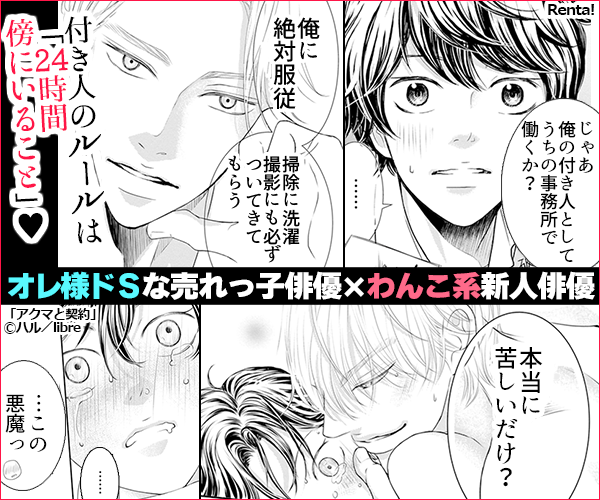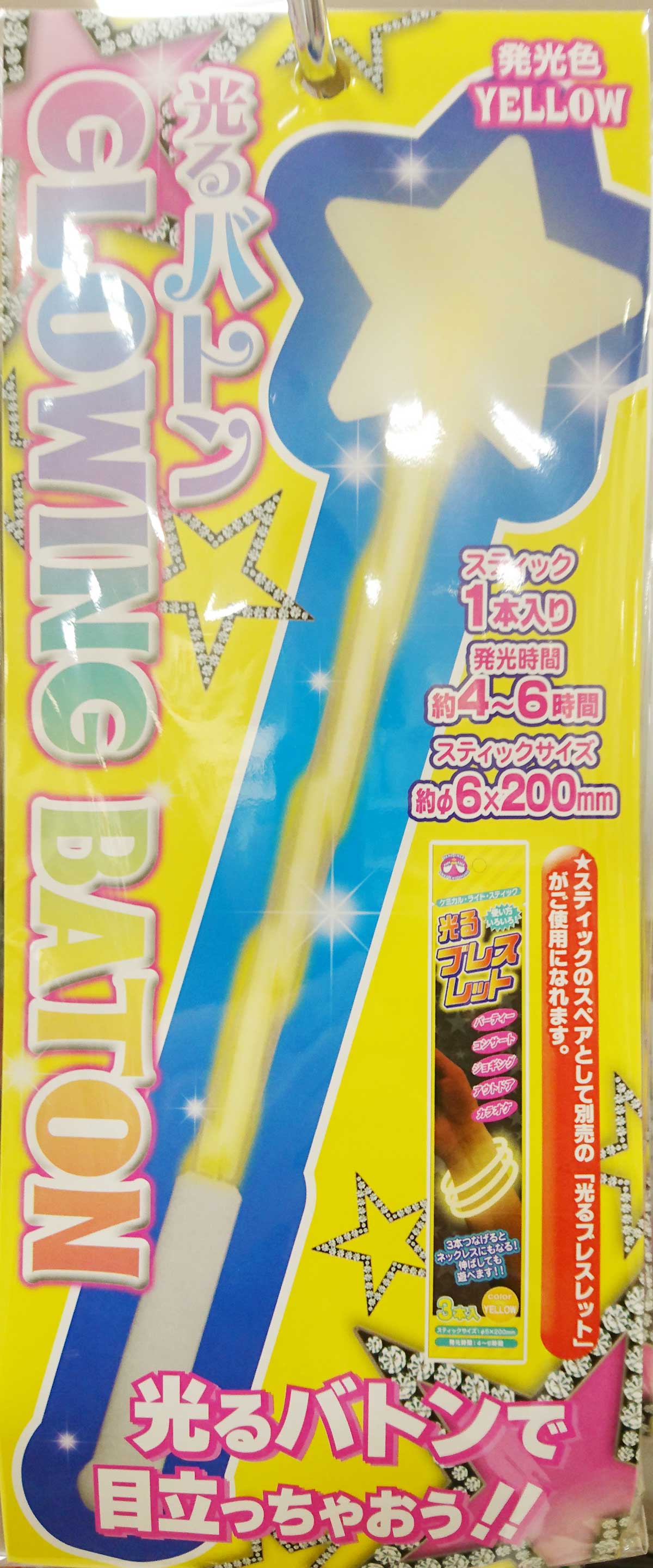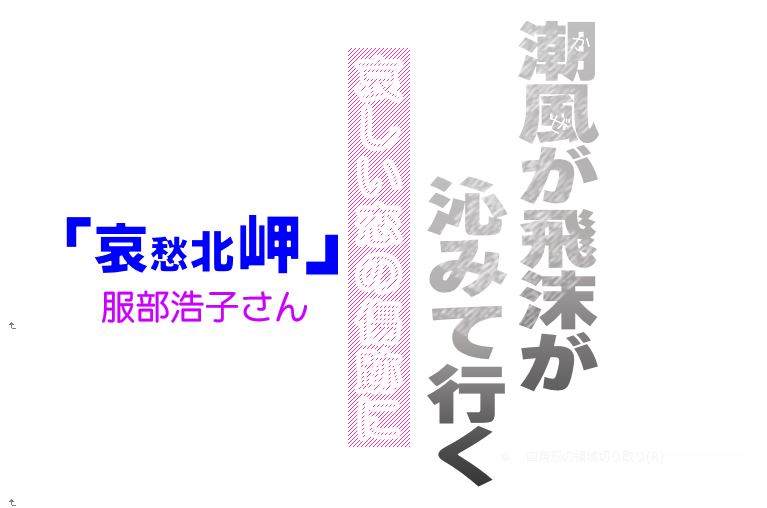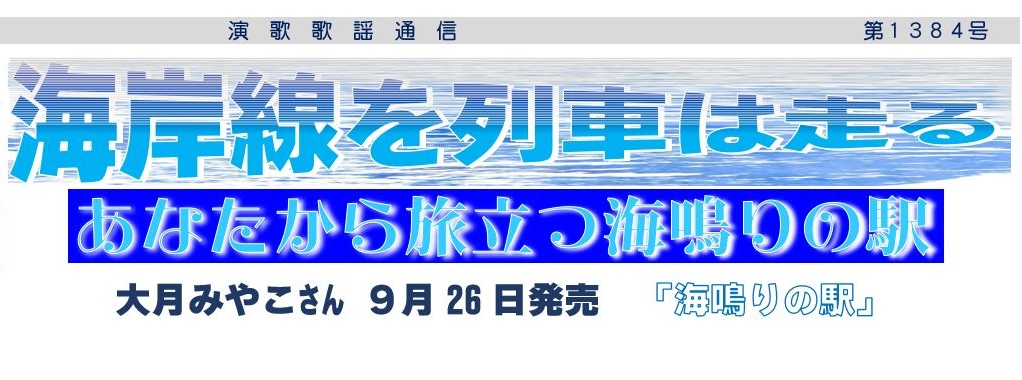
上下の太い文字部分。
「東リベ」27巻発売記念“実現して欲しいグッズ”投票。
地元のショッピングセンターで見かけたカプセルトイのPOPで「ルイカ-09」が使われていました。
「プラモデル塗装には〜ミニチュアキーチェーンに!」の文字ですね。
その下の色の名前も、おそらくルイカですね。
Adobe Fonts経由かもしれませんが、こうして使用例が増えていくのはウレシイ限りです。
「ここなの研究所」という、「鬼滅の刃」に関して考察しているYouTubeチャンネルです。
動画内やサムネイルなどで「ルイカ-09」がたくさん使われています。
Adobe Fontsの仲間入りしてから、使用例が増えてきた感じがします…。
もう1枚だけ。
ウェイト09でも細部が潰れないのはサスガです(自分でいうか笑)。
GYAO!のM-1グランプリ2021のアーカイブ動画などが載っているページです。
「世界最速大反省会」の上下にある金色っぽい文字が「ルイカ」ですね(Adobe Fonts版の09ウェイトかも)。
「こちらもおすすめ」とか、「M-1グランプリ2021 公式サイト」のバナーの白抜き文字もルイカですね。
最後にこれも。
「今年の王者〜特別番組」の部分です。
金色加工、よく似合いますね。
この番組わたしも見てました…。
でも、こんなにルイカ書体が使われていたとは、気づきませんでした…。
SNSオピニオン紙 日刊「ココちゃん通信」 第169号です。
トップ見出し ルイカ
縦見出し ルイカ
ニタラゴレラ
リード  わんぱくレラ
中央   えれがんと平成明朝
写真説明 ニタラゴレラ
縦見出し  ルイカ
囲み 本文 わんぱくレラ
下 セプテンバー
キャパニト えれがんと平成明朝
杉田智和/AGRSチャンネル(YouTube)の字幕にルイカが使われていました。
これですね。
このウェイトってことは、AdobeFontsを利用したかな?
出版物の広告。
上下の大きな文字部分。
AdobeFontsを使用して作成された気がする。
関西テレビの番組『ウラマヨ!』での「ルイカ」書体使用例です。
この番組ではAdobe Fontsで使えるフォントを多く採用しており、そこからセレクトした「ルイカ-09」のようです。
参考にもう1枚だけ。
Adobe Fontsにフォントを提供したことで、このように使用例が増えて、多くの人に知られていけばいいですね!
打首獄門同好会というバンドの楽曲『サクガサク』のミュージックビデオのテロップで「ルイカ」が使われているのを見つけました。
参考にもう1枚。
最後にもう1枚。
ご丁寧に「タイプラボ」とクレジット表記もしてくれています。